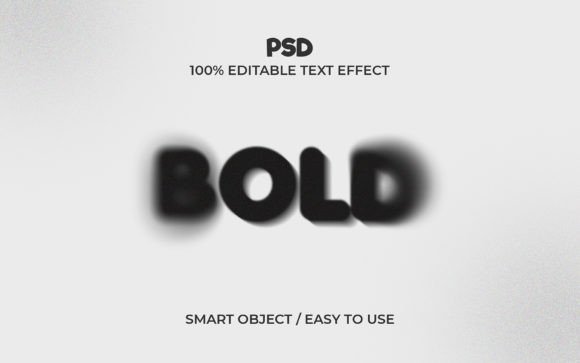
Bold Font Editable PSD Text Effect Style
หากคุณกำลังมองหาเนื้อหาคุณภาพสูงเช่น Bold Font Editable PSD Text Effect Style แพ็คเกจพรีเมียมนี้เป็นตัวเลือกที่ยอดเยี่ยมสำหรับโปรเจ็กต์สร้างสรรค์ของคุณ
ไม่ว่าคุณจะสร้างผลิตภัณฑ์ POD (Print on Demand) คำเชิญงานแต่งงาน หรือกราฟิกโซเชียลมีเดีย Bold Font Editable PSD Text Effect Style ก็เหมาะสมอย่างยิ่ง